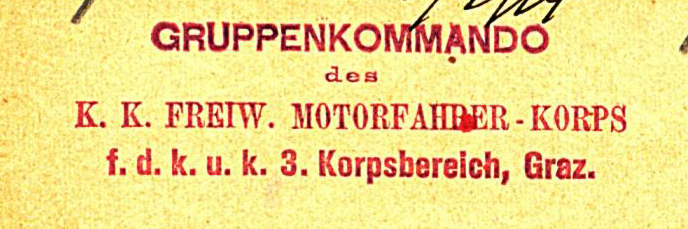
Stempelabdruck um 1910
Ich suche die Schriftarten die bei diesem Stempelabdruck verwendet wurden. Das Dokument auf dem der Stempel angebracht ist stammt von 1913. Die Einheit bestand in dieser Form seit 1910.
Keiner eine Idee welche Schrift das ist? Oder zumindest Tipps für eine ähnliche Schrift? :)
Daswird wohleinfach daran nliegen, dass die AStempelherstellung eben nicht mit Bleisatzschriften geschah, sonder zwar ähnlich wie für den Druck aus Lettern, die aber statt der spiegelverkehrtenerhabenen Buchstaben enen eigentlich Matritzen waren, die dann eben auch nicht von den Bleisatz-Schriftgießereien stammen, sondern eben von Spezialfirmen die den Bedarf der Stempelhersteller bedienten - was zumeist nur einer einmalige Erstaustattung der jeweiligen Schriftart bedeutete.
Anders als diese recht große Revolution in der Drucktechnik ist die Methode, Stempelplatten aus Lettern zu setzen, dann auf diesen Satz  die Gummimasse zu gießen und im Ofen auf den Lettern zu vulkanisieren praktisch geräuschlos zu Ende gegangen, und die Matritzen gingen dann oft achtlos in den Schrott, als der neue Laser-Gravierer in die Werkstatt einzog.
Ich weiss zwar nicht wieso du genau diesen Stempel 'nachmachen' willst aber wenn du mit ähnlichen Schriften leben kannst, dann würde ich diese empfehlen:
und für die Antiqua evtl. diesen: